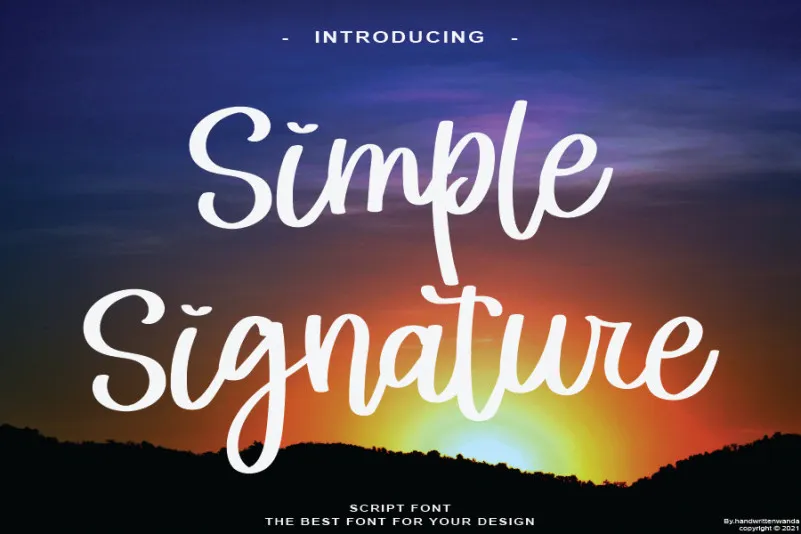
Simple Signature Font – Download Grátis
Esta é uma fonte cíntia bem equilibrada e refinada que transmite sofisticação e elegância. Suas alternativas estilizadas e ligaduras tornam essa fonte a escolha perfeita para qualquer projeto. Leiam atentamente: ‘Simple Signature Script Font’ não pode ser usado com fins comerciais ou de lucro sem autorização do autor/administrador. Sem conhecimento prévio, seu uso sem consentimento poderá resultar em uma multa que será cinco vezes o valor estipulado. Esta fonte deve ser usada apenas para demonstrações (licença de demo). Sua descrição original é clara e direta, destacando a sofisticação e elegância que essa fonte cíntia transmite. Ela também enfatiza as regras importantes sobre o uso comercial. Ao mesmo tempo, ela apresenta uma linguagem informativa e convidativa, como se estivesse escrevendo para um blog de recursos gráficos – um leitor atento e interessado em aprender mais sobre fontes cíntias únicas.